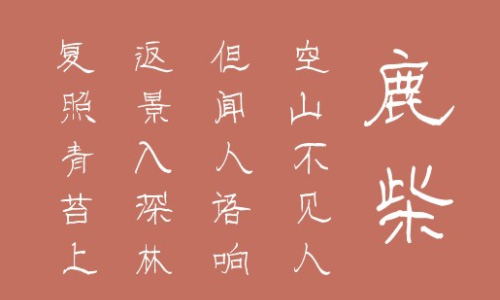
南構(gòu)黃年虎漢隸字體是一款基于篆書演化來的字形,主要將篆書圓轉(zhuǎn)的筆劃改為方折,因為在木簡上用漆寫字很難畫出圓轉(zhuǎn)的筆劃,所以隸書的書寫速度更快,能夠應(yīng)用于文本裝潢、信息展示、網(wǎng)頁設(shè)計、篆刻制模、數(shù)據(jù)制作、裝潢設(shè)計、計算藝術(shù)設(shè)計、視覺設(shè)計、字帖等一切合法應(yīng)用場景,歡迎有需要的朋友們前來下載使用。